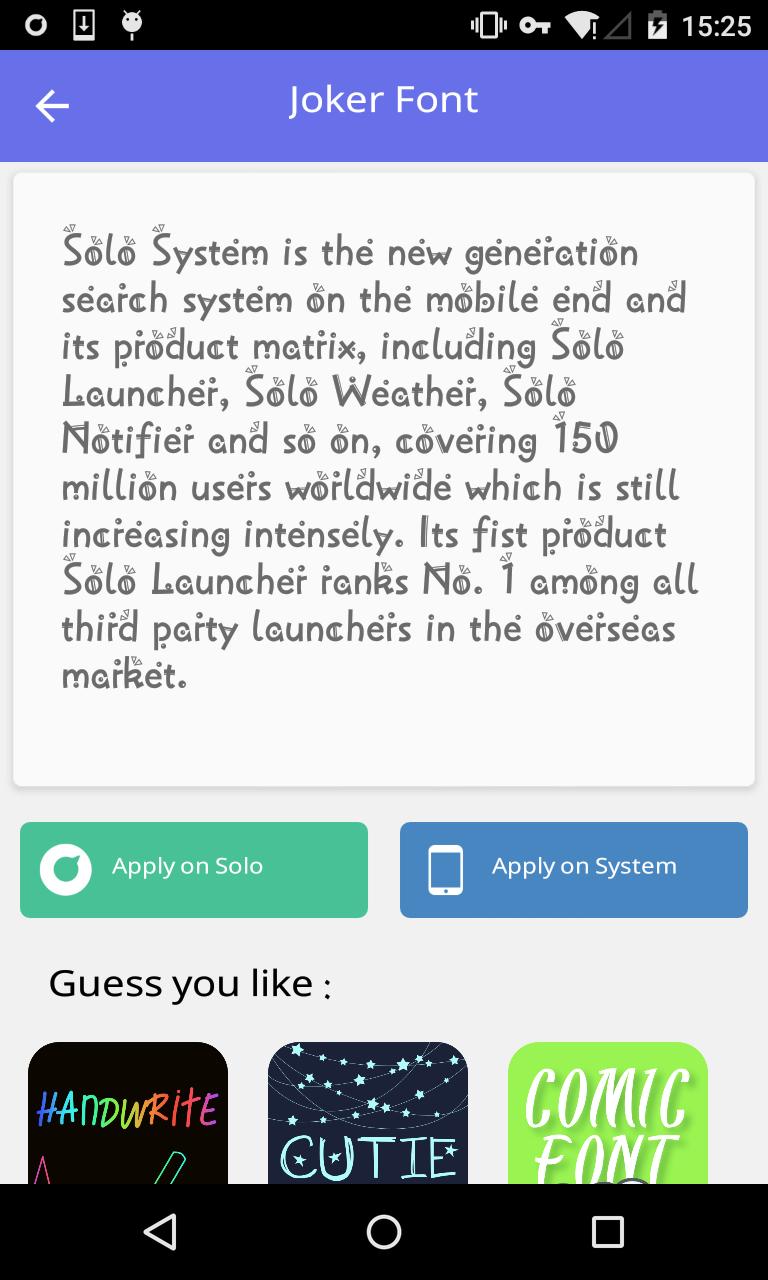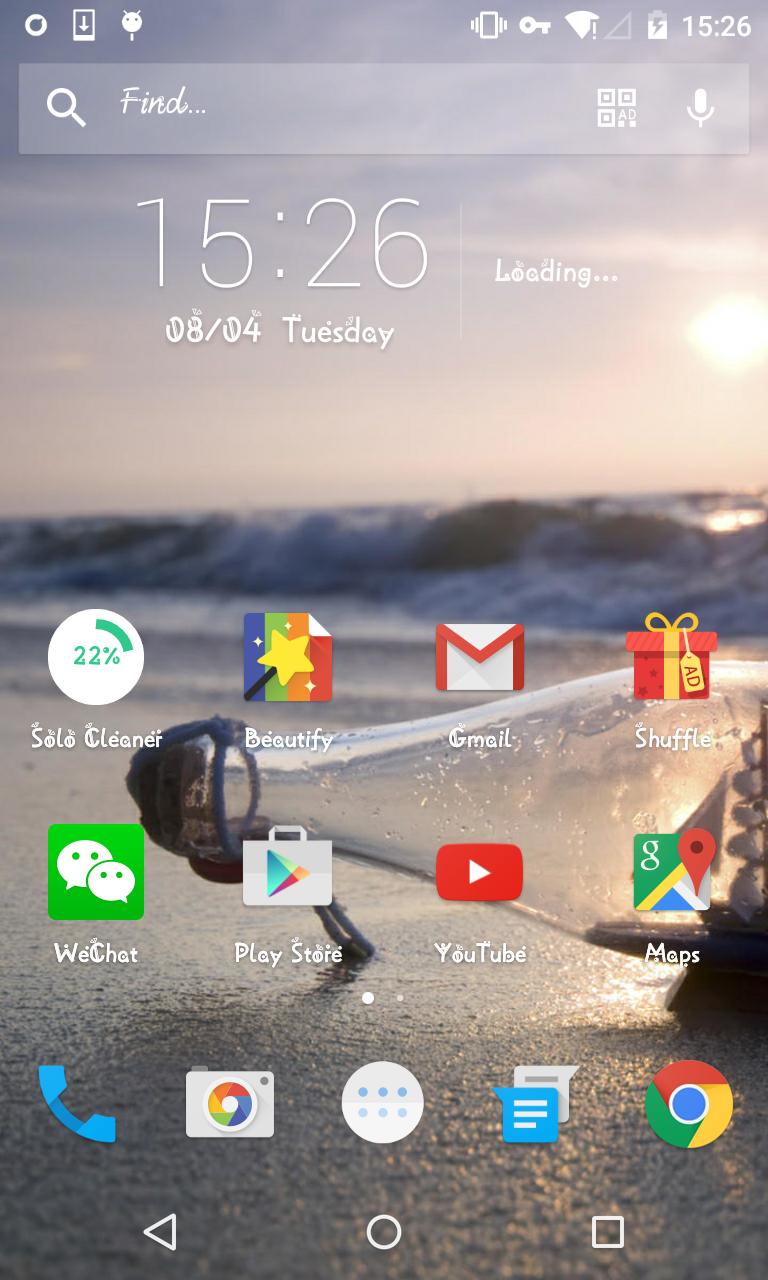
Stylish font #2 - Solo Font
Police élégante gratuite pour le lanceur en solo.
Vous ennuyer avec la police par défaut? Ce pack de polices contient la splendide police élégante gratuitement!
Ce pack de polices est un design pour le lanceur solo . Vous pouvez l'appliquer à tous vos thèmes.
Soutenez plusieurs langues!
Cette police soutient l'anglais, français, allemand, espagnol, portugais, indonésien, malais .etc.
Font de créateur spécial
6. Beaucoup de langues!